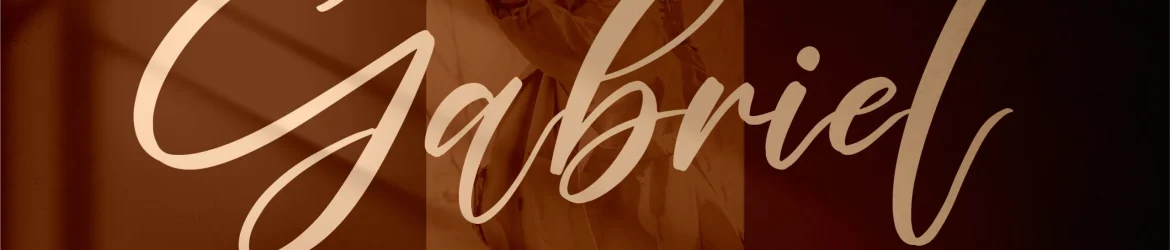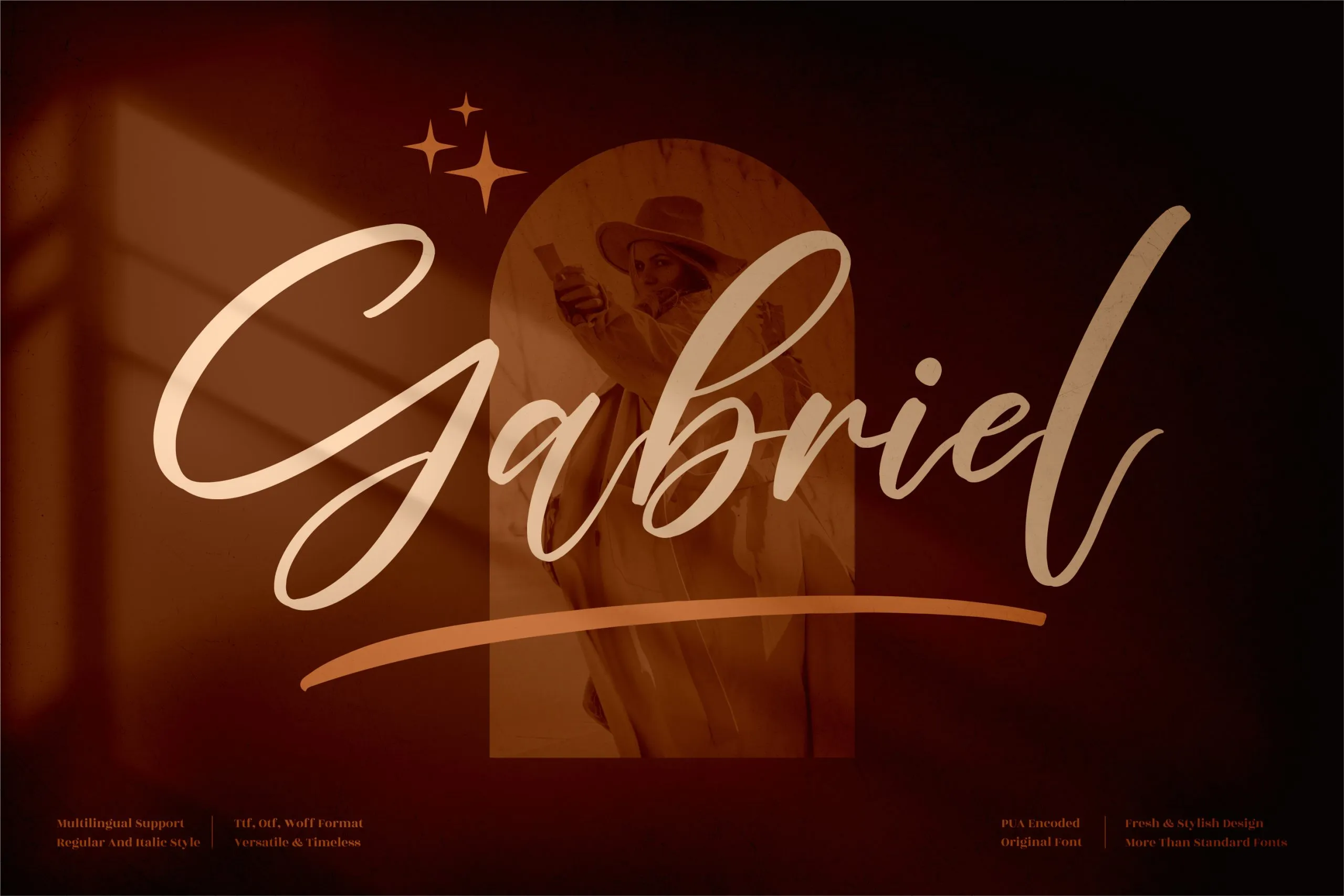
Gabriel Font – Fonte Grátis
Gabriel Font
A fonte Gabriel Font é uma delicada escrita cursiva ideal para diversas aplicações criativas. Suave mas robusta ao mesmo tempo, ela é perfeita para projetos que exigem um toque romântico e elegante. Perfeita tanto para criações em logotipos ou projetos de marca como para designs de acessórios, embalagens de produtos, capas de livros, cartões de nome, convites, cartões de agradecimento, etiquetas, fotografias, marcas d’água e até eventos especiais. Sujeito a um toque delicado que ressalta o seu valor como fonte para projetos pessoais ou profissionais, Gabriel Font é uma escolha perfeita para qualquer designer buscando adicionar uma capa de beleza e elegância à sua arte digital.